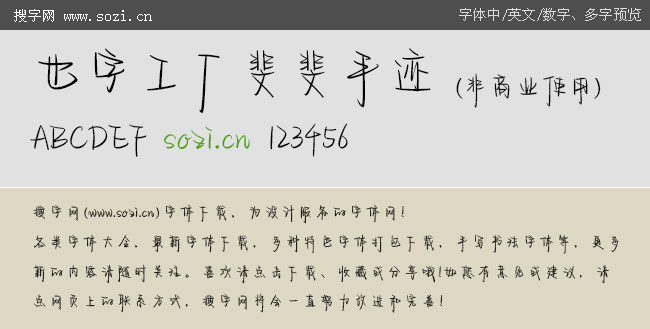
也字工廠斐斐手跡
搜字網(wǎng)給大家提供一款也字工廠斐斐手跡(非商業(yè)使用)中文字體下載,也字工廠斐斐手跡是一款手寫書法字體,字體書寫流暢自然,字形瀟灑大方。具有很好的視覺(jué)效果。適合應(yīng)用于藝術(shù)設(shè)計(jì)、平面宣傳設(shè)計(jì)、網(wǎng)頁(yè)設(shè)計(jì)、海報(bào)設(shè)計(jì)等應(yīng)用(此字體為個(gè)人非商用版,商用可以聯(lián)系:官方網(wǎng)址:https://yefont.com/home,聯(lián)系方式:13798980448)。